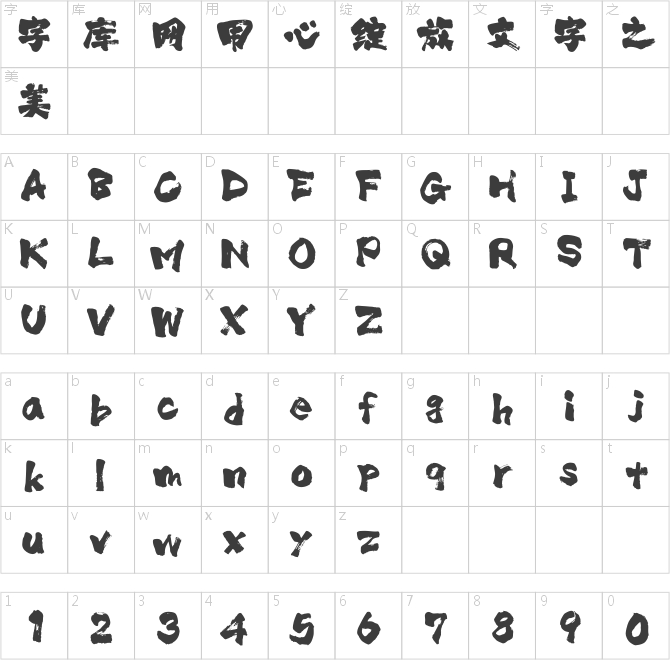
字體名稱: 方正白舟武骨體
方正白舟武骨體的個性沉默、安靜、天真、狂野、憨直、粗暴、倔強,代表男性的形象。這是一款中宮緊湊的方形字體,筆畫粗壯有力,乍看之下像是一個不太成熟的未成年人,同時又呈現出一種穩健自若的精神面貌。運用枯筆書寫出來的白舟武骨飛白鮮明、堅固厚實,給觀者以一種倔強粗獷的印象,適用于大字招牌,和傳統文化類的...